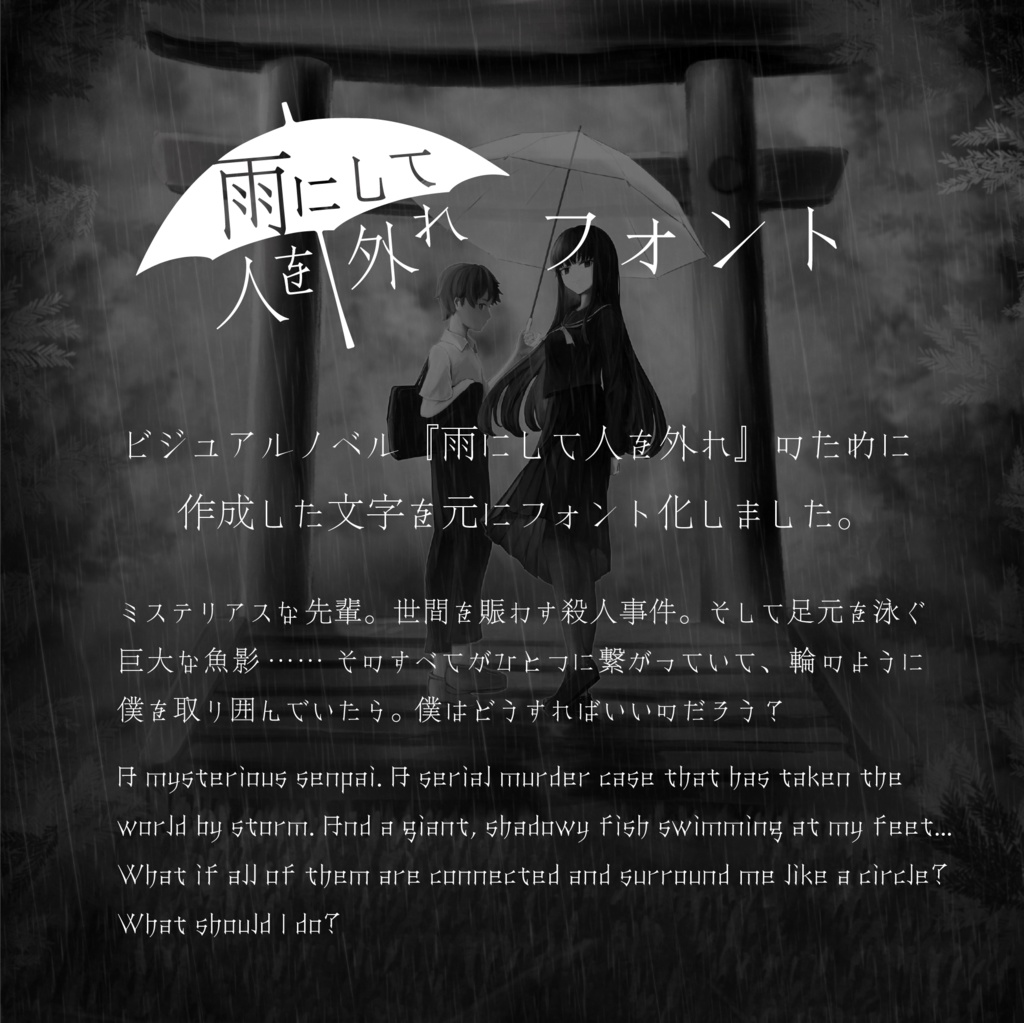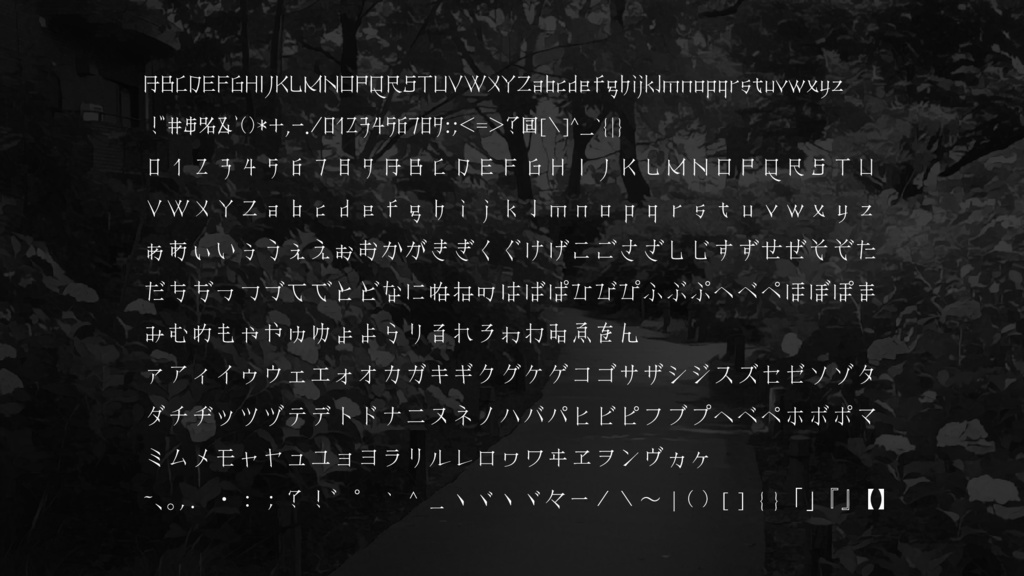
【無料】『雨にして人を外れ』フォント
ビジュアルノベル『雨にして人を外れ』のために作成した文字を元にフォント化しました。 漢字は収録していませんが、モリサワ社の「徐明」をはじめとした宋朝体や明朝体と合わせることを念頭に置いています。 『雨にして人を外れ』はSteamにて無料DLできます! https://store.steampowered.com/app/2168610/_/ D10RAMAではビジュアルノベルを4作品公開しています! https://www.d10rama.com このフォントは無連絡での商用利用可能です。 【重要】投げ銭用バージョンは無料バージョンと全く同一です。 ● 収録文字 !"#$%&'()*+,-./0123456789:;<=>?@[\]^_`{|} ABCDEFGHIJKLMNOPQRSTUVWXYZabcdefghijklmnopqrstuvwxyz 0123456789ABCDEFGHIJKLMNOPQRSTUVWXYZabcdefghijklmnopqrstuvwxyz ぁあぃいぅうぇえぉおかがきぎくぐけげこごさざしじすずせぜそぞただちぢっつづてでとどなにぬねのはばぱひびぴふぶぷへべぺほぼぽまみむめもゃやゅゆょよらりるれろゎわゐゑをん ァアィイゥウェエォオカガキギクグケゲコゴサザシジスズセゼソゾタダチヂッツヅテデトドナニヌネノハバパヒビピフブプヘベペホボポマミムメモャヤュユョヨラリルレロヮワヰヱヲンヴヵヶ ~、。,.・:;?!゛゜`^_ヽヾゝゞ々ー/\~|()[]{}「」『』【】 雨人外 フォントデータ形式:OpenType ● 禁止事項 ・ダウンロードしたこのフォントデータそのものをCD-R、DVD-R等の電磁的記録媒体に一部または全部を記録・複製し、第三者に配布および販売を行うこと。 ・ダウンロードしたこのフォントデータそのものを、インターネット等を通じて第三者に配布および販売を行うこと。